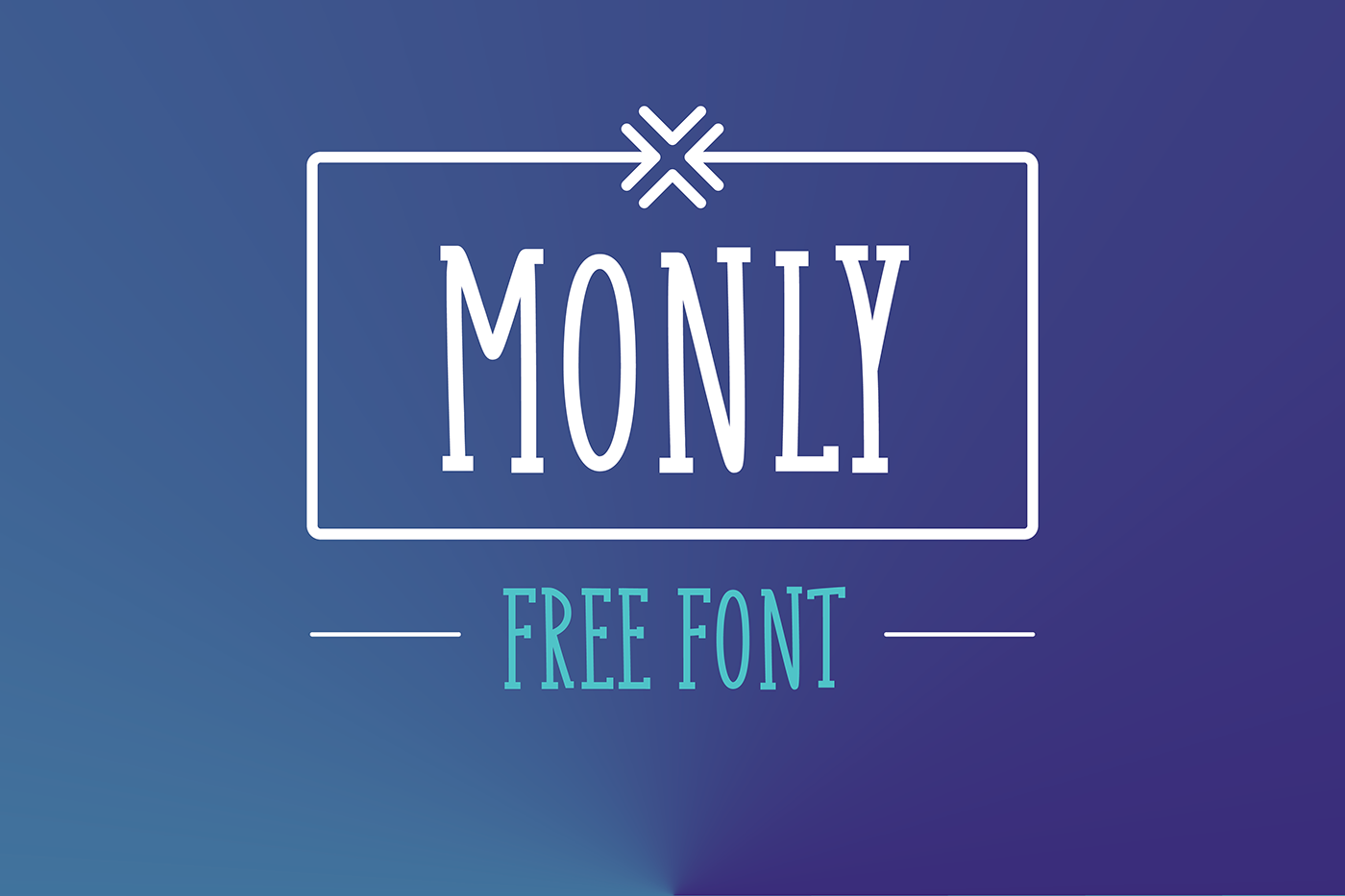
Monly é uma fonte séria e romana leve com uma paixão encantadora. A estrutura desta fonte é baseada na linha única de curva que vai ao longo dela, criando um design versátil e arrojado. Com a inclusão tanto da versão com letras finas quanto da romana, esta fonte oferece uma diversidade impressionante para os projetos digitais. A escolha deste tipo de design é ideal para ambientes onde o leitor pode navegar de forma eficiente, sem ter que se preocupar excessivamente com a aparência das letras. Monly Free font é um presente para designers que procuram uma solução fácil e gratuita para usar em projetos pessoais e comerciais.
Designer: Gatis Vilaks